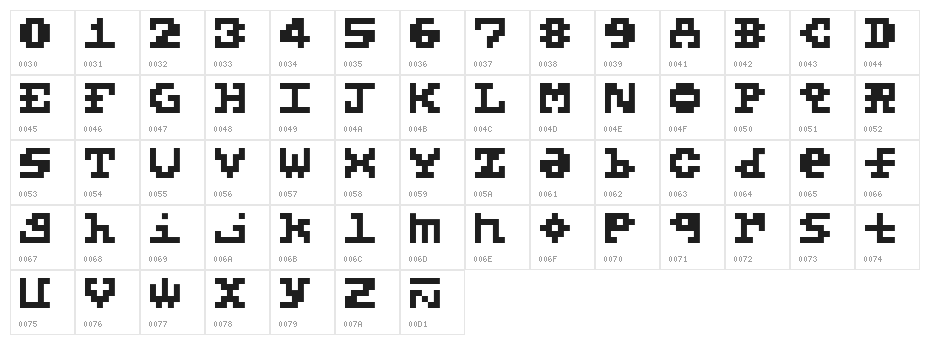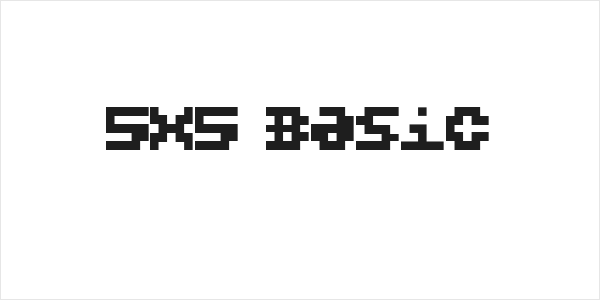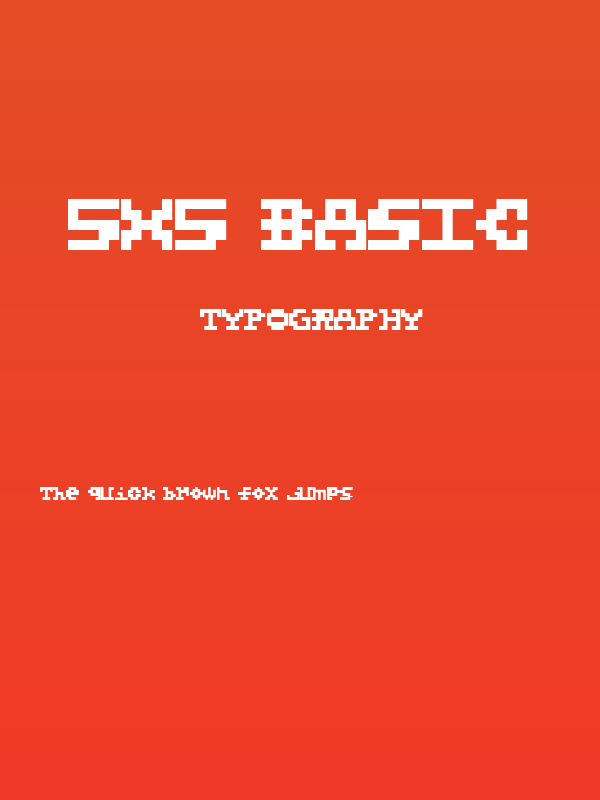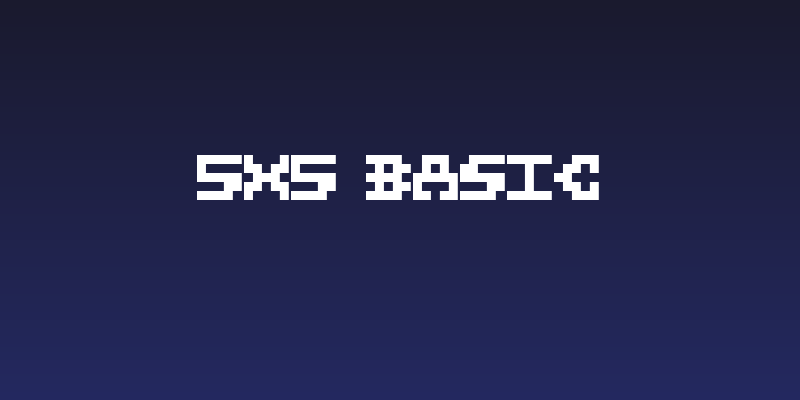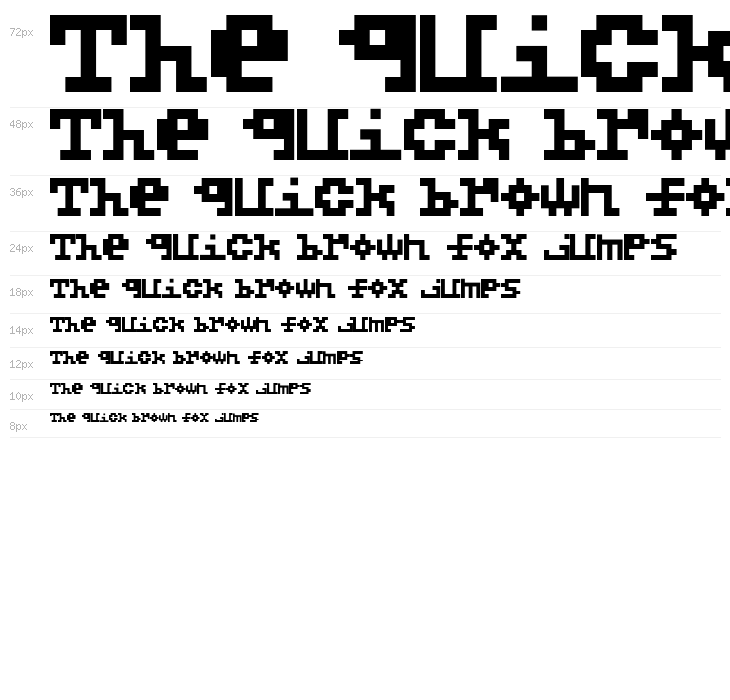
5X5 Basic Font
| Kategorien | Pixel |
| Zeichenabstand | Normal |
| Gesamtstil | Vintage |
| Anwendungsfall | Headlines, Logos, Digital Art |
| Vorgeschlagene Projekte | Ideal for retro-themed designs, video game graphics, digital art projects, and any creative work that aims to evoke a sense of nostalgia for early digital technology. |